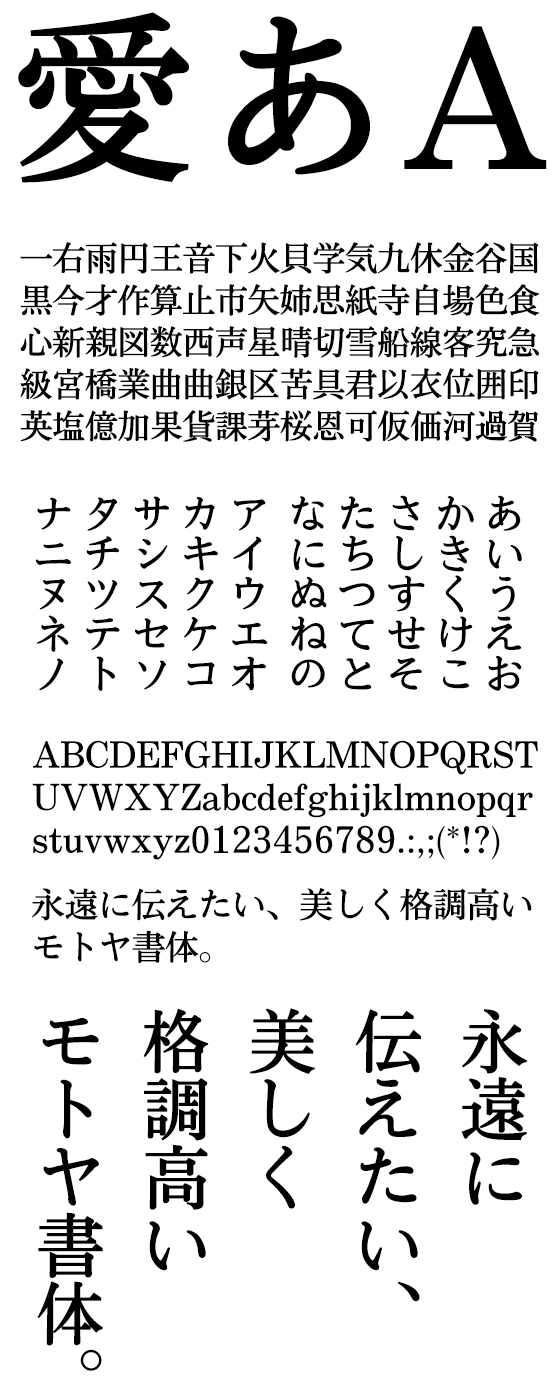
明朝体
株式会社モトヤ
NUDモトヤ明朝5 LiteN
NudMotoyaMinchoLiteN-W5
本文用は懐をバランス良く広く、見出し用は縦画の下にふくらみを持たせ楷書風の柔らかさを表現した、伝統的な明朝体です。
モトヤUDフォントは、大文字化対応や太さの調整、シンプルな文字構成で通常のフォントより可読性・視認性・判読性に優れており、医療分野/組込み機器表示/各種パッケージでの利用に最適です。